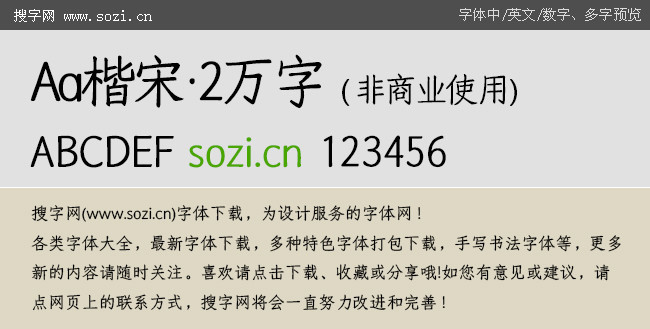
Aa楷宋·2萬(wàn)字
搜字網(wǎng)給大家提供一款A(yù)a楷宋·2萬(wàn)字(非商業(yè)使用)中文字體下載,該字體是一款簡(jiǎn)潔的字體,字體空間分布均勻,筆觸適中,書寫端正。適合書裝設(shè)計(jì)、包裝設(shè)計(jì)、海報(bào)設(shè)計(jì)等應(yīng)用(此字體為個(gè)人非商用版,商用可以聯(lián)系QQ:1006760504)。